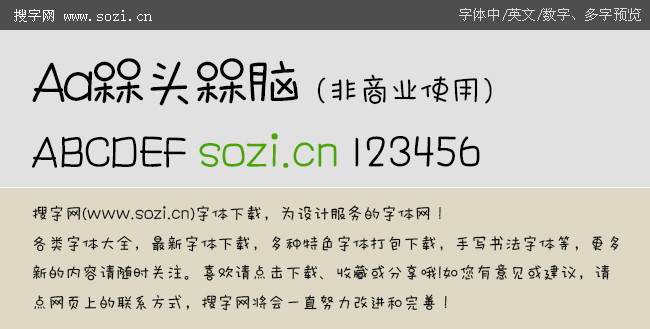
Aa槑頭槑腦
搜字網(wǎng)給大家提供一款A(yù)a槑頭槑腦(非商業(yè)使用)中文字體下載,Aa槑頭槑腦是一款卡通風(fēng)格的手寫字體,這款字體字形圓潤(rùn)可愛,富有趣味性,具有很好的視覺感。適合應(yīng)用于藝術(shù)設(shè)計(jì)、平面宣傳設(shè)計(jì)、網(wǎng)頁設(shè)計(jì)、海報(bào)設(shè)計(jì)等應(yīng)用(此字體為個(gè)人非商用版,商用可以聯(lián)系QQ:1006760504)。